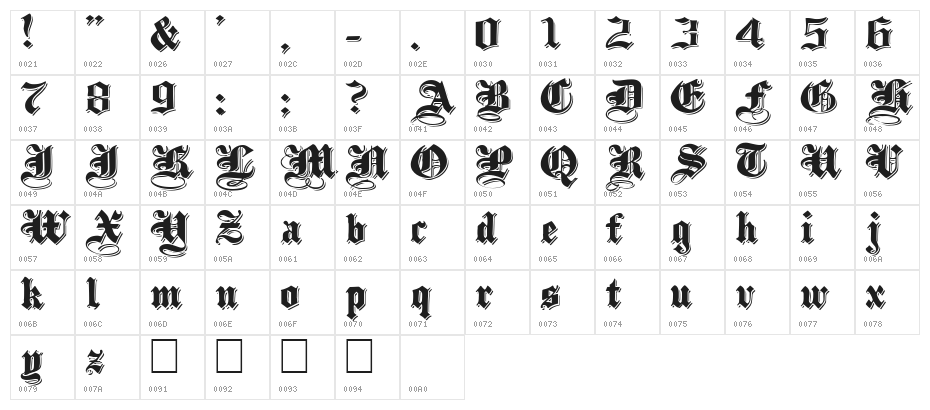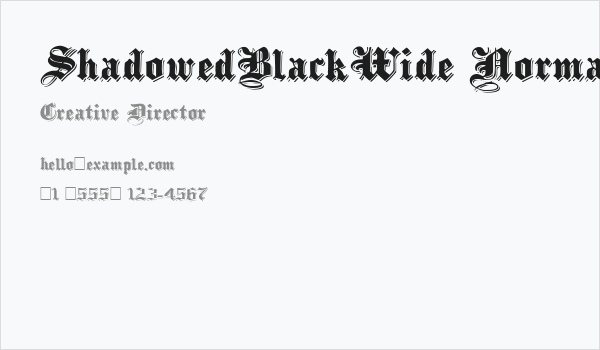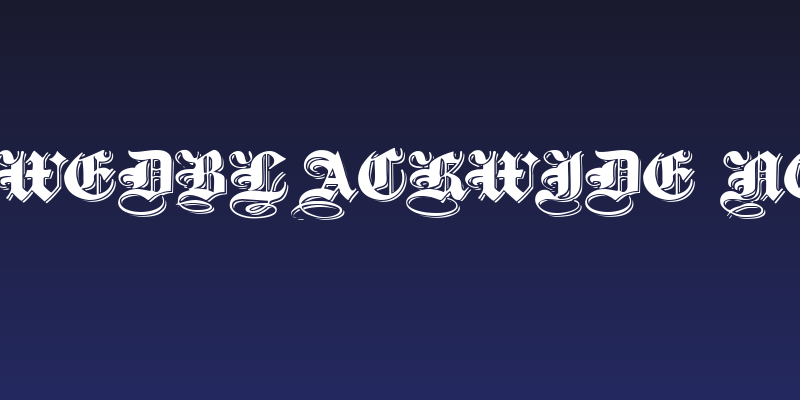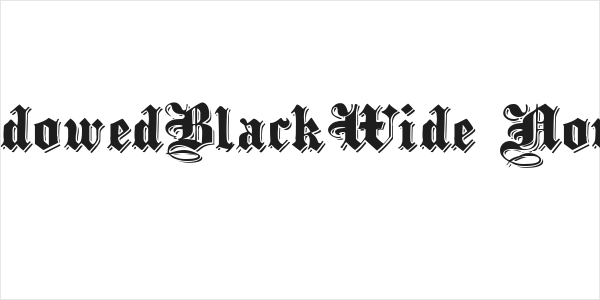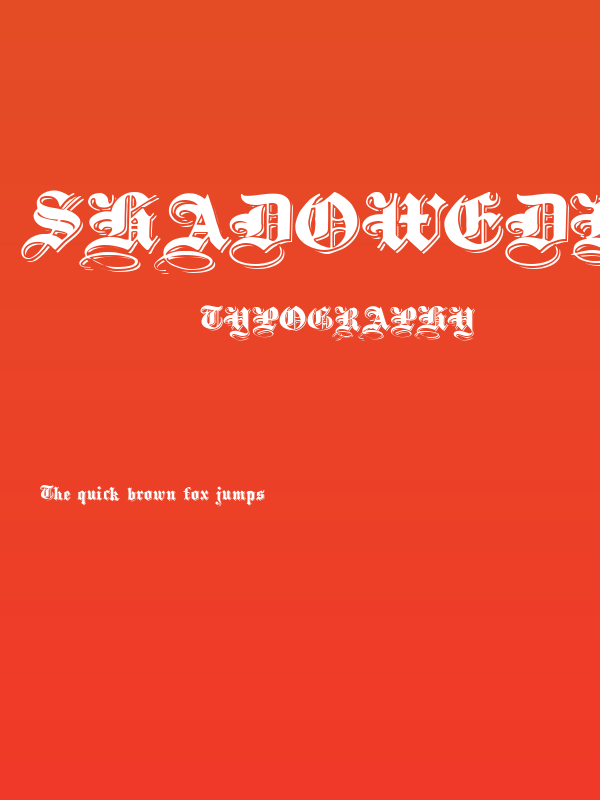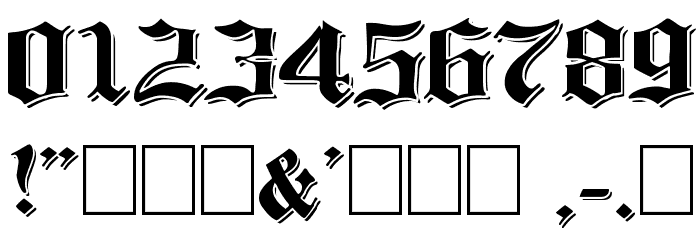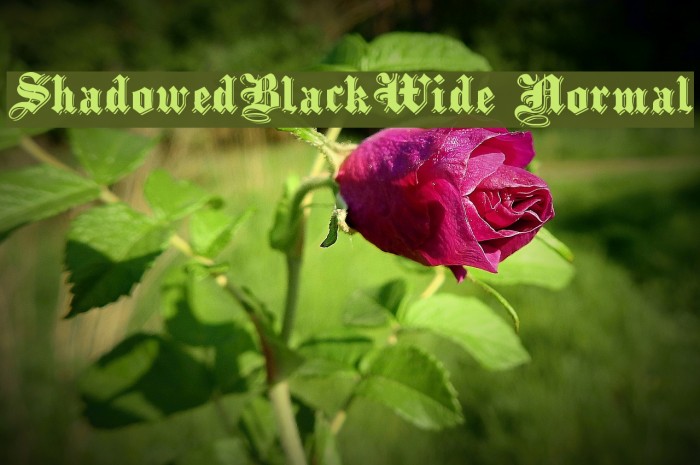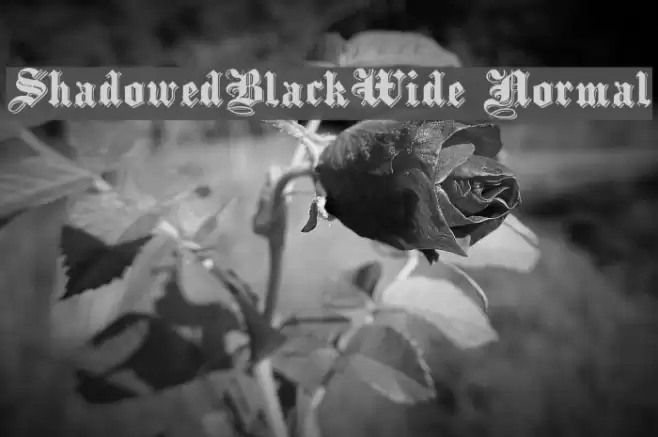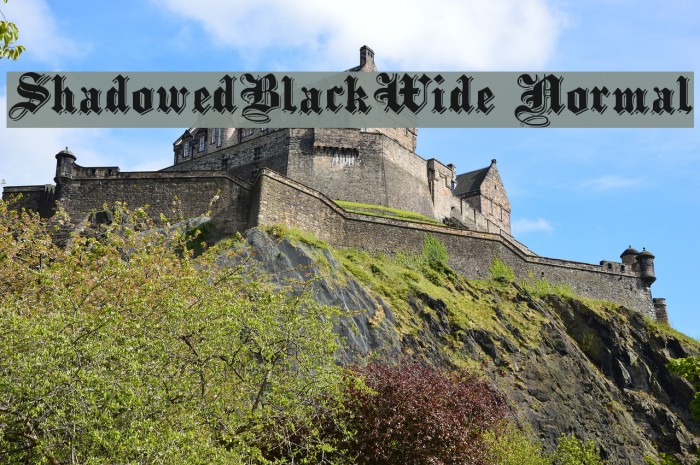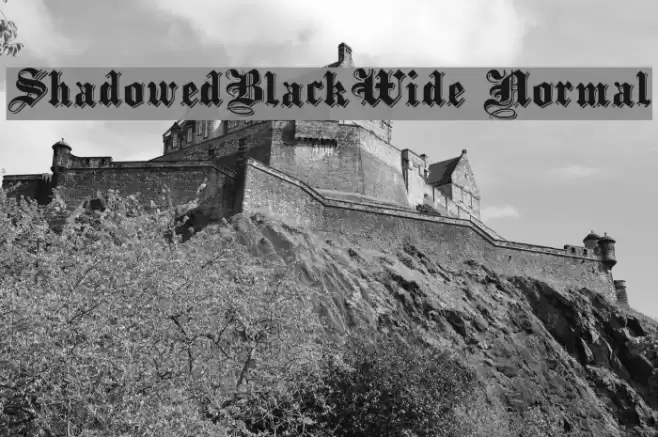
ShadowedBlackWide Normal Font
✎ Old fashioned
| カテゴリ | Old fashioned |
| 用途 | Headlines, Logos, Decorative text |
| おすすめプロジェクト | Ideal for projects requiring a historical or gothic aesthetic, such as event posters, book covers, or branding for luxury products. |